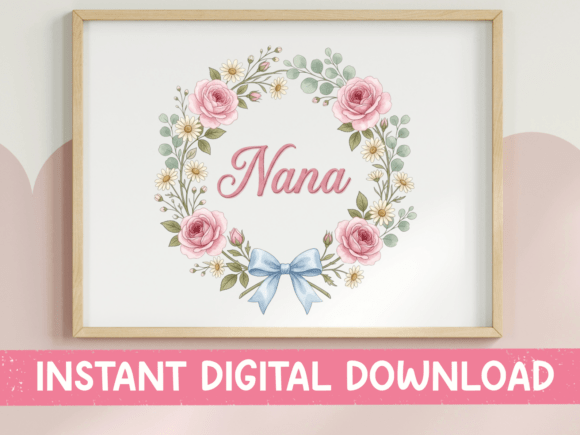
Nana Floral Wreath Script Design
Die richtigen Designelemente zu finden, kann eine Herausforderung sein, aber Nana Floral Wreath Script Design bietet eine außergewöhnliche Sammlung, die Ihre Arbeit sofort aufwertet.